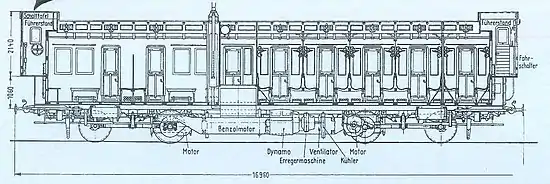
Чертёжный шрифт
Чертёжный шрифт — рукописный и компьютерный шрифт, который применяется для оформления чертежей и других технических документов. Шрифт стандартизован, его описывает международный стандарт ISO 3098 и такие национальные стандарты, как ГОСТ 2.304-81 и DIN 6776-1. Надписи чертёжным шрифтом могут выполняются от руки с использованием прямоугольной или наклонной сетки, могут использоваться трафареты и сухой перенос, а также компьютерный набор.[1]
Стиль | рублёный, пропорциональный, минималистичный |
Классификация | технический |
Использование | в чертежах |
Набор символов | русский, латинский, греческий алфавиты, технические символы |
Согласно требованиям системы стандартов ЕСКД все надписи на чертежах должны быть выполнены чертёжным шрифтом по ГОСТ 2.304-81, а в текстовых документах чертёжный шрифт должен использоваться при рукописном способе выполнения[2].
Стандарт устанавливает высоту и ширину символов, толщину линии, расстояния между символами строками и словами.
ISO 3098 и ГОСТ 2.304-81 определяет написание для латинского, кириллического и греческого алфавитов, арабских и римских цифр.
История
До 1840-х гг. надписи на чертежах в России выполнялись теми же почерками, что и обычные документы, с редким применением букв гражданской печати[3]. После этого на чертежах появляются художественные шрифты (готические, славянские, курсивы и др.)[3], которые в 1870-е гг. во многом сменила разработанная Фридрихом Зённекеном модификация старинного французского шрифта «рондо» (Rundschrift)[4]. С увеличением производства чертежей и распространением светокопирования, синек вскрылись недостатки шрифта рондо: он был труден для исполнения, а его тонкие элементы в мелком кегле исчезали на копиях[3].
Ещё в 1895 году американец Чарльз Рейнхардт предложил использовать для рабочих чертежей максимально простой и практичный шрифт с одинаковой толщиной штрихов[5]. В 1900-е гг. стали появляться целлулоидные шрифтовые трафареты, которые позволили легко писать на чертежах буквы и цифры, отвечающие требованиям простоты и минимальной контрастности (малого контраста)[4], а Прусские железные дороги приняли стандарт Musterzeichnung IV 44 на шрифты для надписей на вагонах, схемах и чертежах, а вскоре также и вывесок на станциях[6]. В 1919 году на основе железнодорожного стандарта основанный двумя годами ранее Комитет по стандартизации немецкой промышленности установил первые в мире стандарты DI-Norm (DIN) 16 для наклонного и DIN 17 для прямого чертёжных шрифтов[6].
В 1928 году Комитет по стандартизации при Совете труда и обороны СССР опубликовал разработанный годом ранее Комиссией по нормализации чертежей при ВСНХ общесоюзный стандарт (ОСТ) № 353 с наклонным (75°) «нормальным» чертёжным шрифтом, который имел рекомендательный характер и изначально не получил широкого распространения[3]. После введения в шрифт «круглых» строчных букв он был в 1934 утверждён ОСТ ВКС 7535 в качестве обязательного для всех чертежей в машиностроении и несмотря на внесение незначительных изменений в 1941 (ОСТ 7535—39), 1946 (ГОСТ 3554—46), 1953 (ГОСТ 3554—52) и 1959 (ГОСТ 3554—59) годах просуществовал почти в исходном виде до введения ЕСКД в 1968 году.
Стандарты
Международный стандарт ISO 3098 состоит из шести частей под общим наименованием «Документация техническая на продукцию. Шрифт для надписей и обозначений»:[7][8]
- ISO 3098-1:2015 Общие требования
- ISO 3098-2:2000 Латинский алфавит, цифры и знаки
- ISO 3098-3:2000 Греческий алфавит
- ISO 3098-4:2000 Диакритические и специальные знаки для латинского алфавита
- ISO 3098-5:1997 Шрифт из букв латинского алфавита, цифр и знаков для систем автоматизированного проектирования
- ISO 3098-6:2000 Кириллица
Входящий в Единую систему конструкторской документации (ЕСКД) межгосударственный стандарт ГОСТ 2.304-81 Шрифты чертёжные введён в 1982 году, полностью соответствует стандартам Совета экономической взаимопомощи СТ СЭВ 851-78-СТ СЭВ 855-78 и заменяет предшествовавший стандарт ГОСТ 2.304-68.
Стандарт Немецкого института стандартизации DIN 6776-1 «Чертежи технические. Надписи, шрифтовые знаки» соответствует стандарту ISO 3098.
Размеры
Высота шрифта
Размером шрифта называется высота прописных (заглавных) букв в миллиметрах. Размер (высота) шрифта обозначается буквой h.
Стандарт устанавливает следующие размеры шрифта: 1,8; 2,5; 3,5; 5; 7; 10; 14; 20; 28; 40 (каждый следующий размер больше предыдущего приблизительного в раз). Размер 1,8 не рекомендуется, но допускается. Размеры 1,8 и 2,5 не допускаются, если чертёж выполняется карандашом. Для стандартного чертежа предпочтительными являются размеры 3,5; 5 и 7. Высота строчных букв равна предыдущему размеру шрифта. Так, если размер шрифта — 10, то высота прописных букв — 10 мм, а высота строчных —7.
Выносные элементы
Термин «высота шрифта» не учитывает выносных элементов символов, которые выполняются за счёт промежутков между строками. В кириллице выносные элементы имеют прописные буквы Д, Й, Ц, Щ и строчные буквы (буква Ё в ГОСТ 2.304-81 не упоминается).
Толщина линии шрифта
Толщина линии шрифта обозначается буквой d.
Существуют два типа шрифтов — тип А, у которого толщина линии в 14 раз меньше его размера (d = 1/14 h) и тип Б (в ISO 3098 обозначается латинской «B»), у которого толщина линии в 10 раз меньше его размера (d = 1/10 h). Поскольку ширина шрифта прямо пропорциональна толщине линии, шрифт А более узок, чем Б.